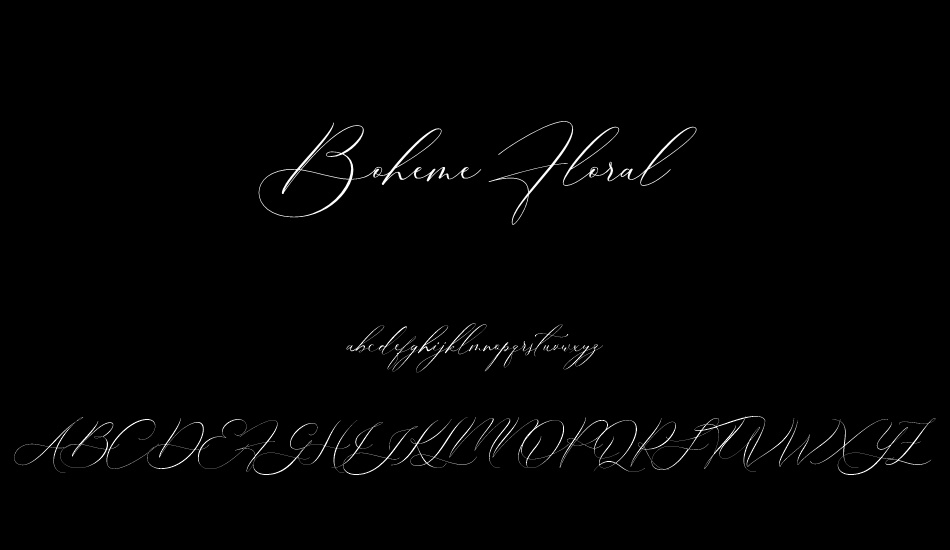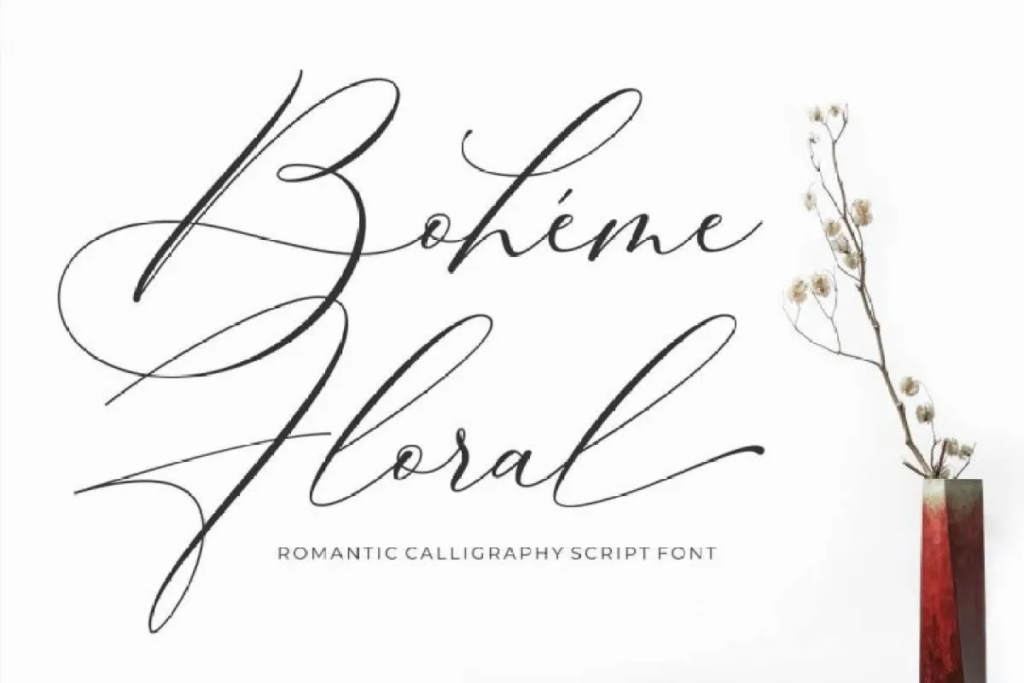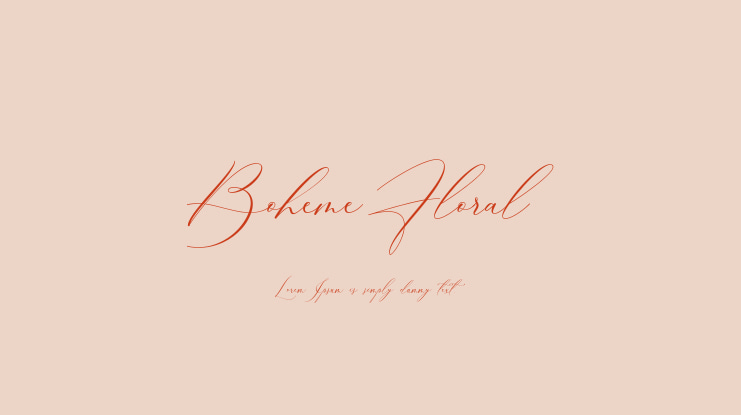
Font Boheme Floral là bộ phông chữ thuộc dòng Botanical Script đầy chất thơ, kết hợp khéo léo giữa nét viết tay mềm mại và các họa tiết cành lá, nụ hoa tự nhiên điểm xuyết trên từng ký tự. Với phong cách lãng mạn, thanh tao và đậm chất Bohemian, font Boheme Floral Việt hóa là chất liệu trực quan tuyệt vời để các kiến trúc sư, nhà thiết kế mang hơi thở cỏ cây vào các bản vẽ phối cảnh biệt thự nhà vườn, quán cafe nhà kính hay biển hiệu spa thảo mộc.
Họa tiết hoa lá tự nhiên và chất thơ tinh tế của font Boheme Floral
Điểm cuốn hút của font Boheme Floral nằm ở nghệ thuật lồng ghép các đường nét thực vật uốn lượn vào cấu trúc chữ cái một cách hữu cơ, tạo cảm giác như từng con chữ đang đâm chồi nảy lộc. Nét chữ sở hữu độ thanh mảnh nhẹ nhàng, các đường cong mềm mại gợi liên tưởng đến những dải dây leo xanh mướt trong các khu vườn thảo mộc châu Âu.
Sự ổn định về mặt cảm xúc của dòng font này giúp khơi gợi sự an yên, tĩnh tại và giải tỏa căng thẳng cho người ngắm nhìn. Khi xuất hiện trên các vật liệu kiến trúc thân thiện môi trường như gỗ mộc sáng màu, kính hoa đồng, vải lanh thô hay vách tường xanh trong các công trình nhà lắp ghép sinh thái, Boheme Floral tạo nên sự giao thoa thẩm mỹ dịu dàng.
| Phân loại phong cách | Botanical Script / Floral Calligraphy / Boho Chic |
| Mục đích phù hợp | Biển tên spa, menu cafe nhà kính, thiệp sự kiện |
Tư vấn từ chuyên viên: Boheme Floral sở hữu nhiều chi tiết hoa lá trang trí tinh xảo. Để bản thiết kế đạt hiệu quả thẩm mỹ tốt, bạn nên sử dụng phông chữ này cho các tiêu đề chính, lời tựa ngắn hoặc tên thương hiệu. Phần nội dung mô tả kỹ thuật chi tiết nên đi kèm một phông chữ không chân thanh mảnh hơn để người xem tiếp nhận thông tin dễ dàng.
03 Ứng dụng phông chữ Boheme Floral vào công trình thực tế
Nhờ vẻ ngoài thanh thoát và tính gợi hình hoa lá phong phú, bộ phông chữ này mang lại giá trị thực tế lớn trong khâu tạo điểm nhấn cho các công trình hiện đại:
- Hệ thống biển hiệu cho Spa Thảo Mộc và Quán Cafe Nhà Kính: Những nét chữ đính kèm nụ hoa của Boheme Floral rất ăn ý khi gia công chữ nổi bằng inox vàng gương hoặc khắc chìm trên gỗ thông, giúp mặt tiền công trình toát lên vẻ thư thái và thuần khiết.
- Bảng chỉ dẫn và Biển tên phòng Khu nghỉ dưỡng sinh thái: Phông chữ này khi in trên kính mờ hoặc bảng gỗ treo sẽ giúp các căn homestay lắp ghép giữa đồi hoa toát lên vẻ lãng mạn, tạo cảm giác gần gũi cho du khách lưu trú.
- Bìa hồ sơ ý tưởng cảnh quan sân vườn: Sử dụng tải font Việt hóa Boheme Floral cho tên dự án và tiêu đề các phối cảnh xanh giúp hồ sơ trông như một cuốn nhật ký thảo mộc tinh tế, tạo thiện cảm lớn với chủ đầu tư.
03 Lưu ý bố cục font Việt hóa Boheme Floral giữ trọn vẻ thanh tao
Để khai thác hiệu quả vẻ đẹp của dòng font hoa lá này mà không gây cảm giác rườm rà cho bản vẽ, người thiết kế nên lưu tâm một số kinh nghiệm sau:
- Tránh viết hoa toàn bộ ký tự: Các chữ hoa của Boheme Floral có các cành lá uốn lượn lớn. Việc viết hoa liên tiếp nhiều chữ cái sẽ làm các nhánh hoa đè lên nhau, gây mất bố cục và làm câu văn trở nên khó đọc.
- Bố trí khoảng thở rộng rãi: Do nét chữ có các nhánh lá vươn ra ngoài, bạn nên chừa khoảng trống thoáng đãng xung quanh tiêu đề để các chi tiết hoa lá được hiển thị trọn vẹn, không bị che khuất bởi các chi tiết đồ họa phụ trợ.
- Lựa chọn gam màu tự nhiên dịu nhẹ: Boheme Floral phát huy hiệu quả thị giác cao khi phối cùng các tông màu mang sắc thái thiên nhiên như xanh rêu nhạt, hồng pastel, vàng đất hoặc trắng kem, làm nổi bật đường nét hữu cơ của bộ chữ.